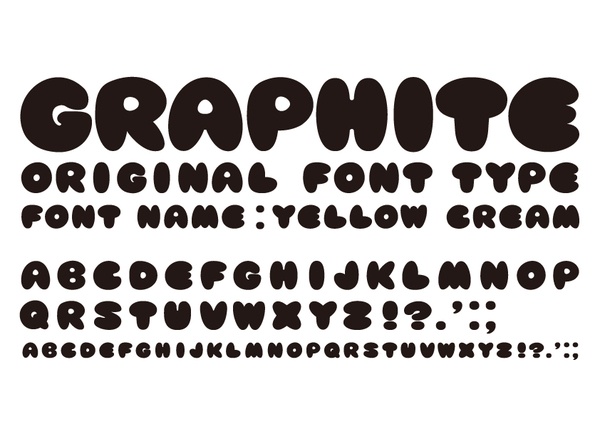
ТОП 10 шрифтов Бабл (пузыри) c поддержкой кириллицы
Шрифты в виде пузырей или «бабл», bubble – это декоративные шрифты, используемые для небольших фрагментов текста, заголовков, слоганов. Их используют обычно в детских проектах, кинематографических, если подходят к общей стилистике и прочих. Буквы таких шрифтов имитируют пузырики разных форм и размеров, от круга до овала, большие и маленькие.
Мы подобрали для вас 10 лучших и аутентичных бабл шрифтов с поддержкой кириллицы, которые представляют как объёмные буквы, так и жирные, которые кажутся объемными (визуально заметна разница). Есть даже декоративный шрифт, в котором вместо букв разные наборы пузырей, но исключительно в английском варианте. Есть и шрифты с дополнительным декором. Так или иначе, но работая над любым подходящим проектов в Photoshop, эти бабл шрифты смогут вам помочь.
Bubbleboddy Neue
Airfool
a_JasperTtlRndDrNord
a_BighausTitulBrkHll
Asylbek
Bubble
Dolores Cyr
Testo
Get Coffee
Sutturah